コピペできない“木”02「幅と高さ」
「村榑樹」など木偏では「木」が縦長になりますが、右側に来る要素に合わせて「木」の幅を細かく変えています。逆に、高さの調整が必要な「宋栄榮」などの漢字もありますし、「棊」のように被さる要素と合わせるときは幅と高さ両方の調整をします。さらに「保新欝」などであれば小さな「木」が必要です。
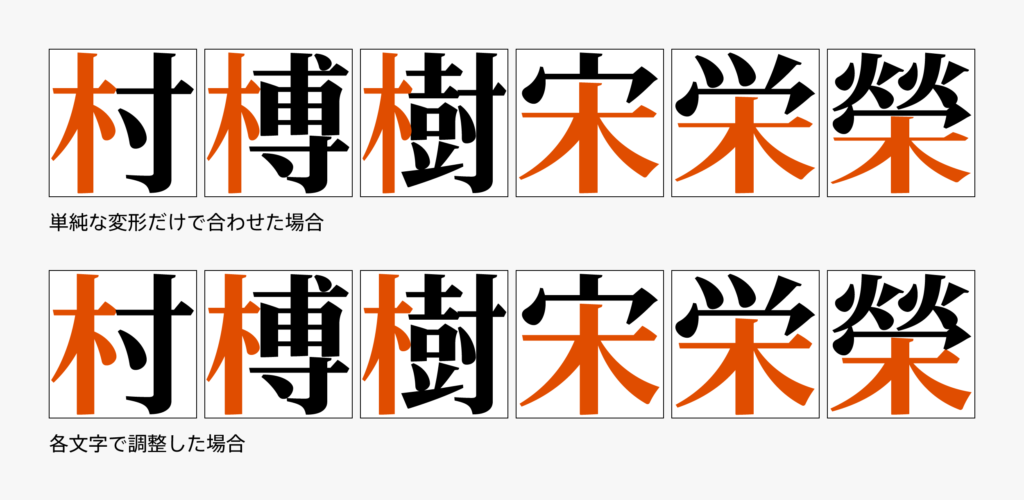
一緒になる要素とぶつかってしまうなら、一部の筆画を切るようにして混雑を回避することもあります。このように漢字制作では様々な形状の「木」が必要で、それを単純な変形だけで対応すると骨格が歪んでしまったり太さが合わなかったり先端の角度が不自然だったりとなかなか上手くいきません。一文字一文字に合わせて丁寧にアウトラインを調整していきます。